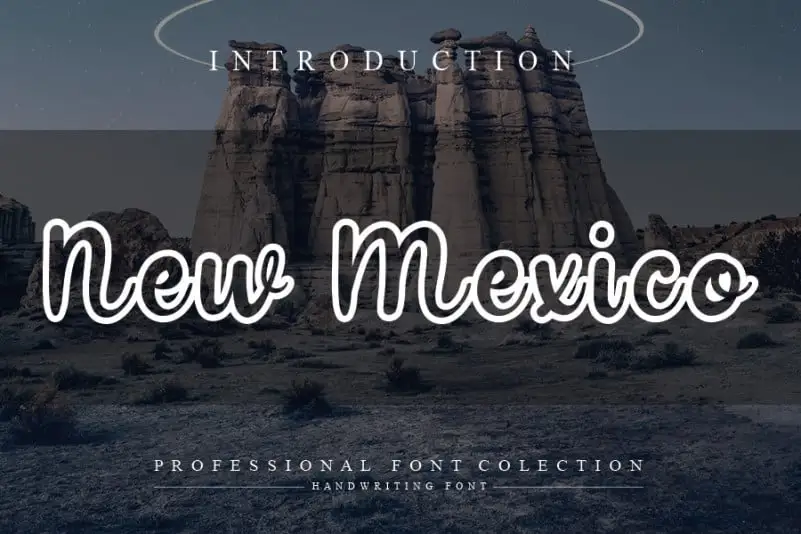
Nova Mexico Script Font é uma fonte escrita a mão ideal para aqueles que buscam uma maneira única de trazer vida a seus projetos de design. Esta elegante fonte não apenas oferece um toque sofisticado, mas também pode ser usada em uma ampla variedade de aplicativos, desde as identidades de marca e selos de casamento até assinaturas e logotipos. Seja para estilizar cabeçalhos ou criar um design de convites personalizado, a Nova Mexico Script Font está aqui para garantir que seu trabalho brilha em qualquer projeto. Este é o ideal para quem busca uma fonte escrita a mão moderna e sofisticada que se adequa a diversos usos, tanto pessoais quanto profissionais.